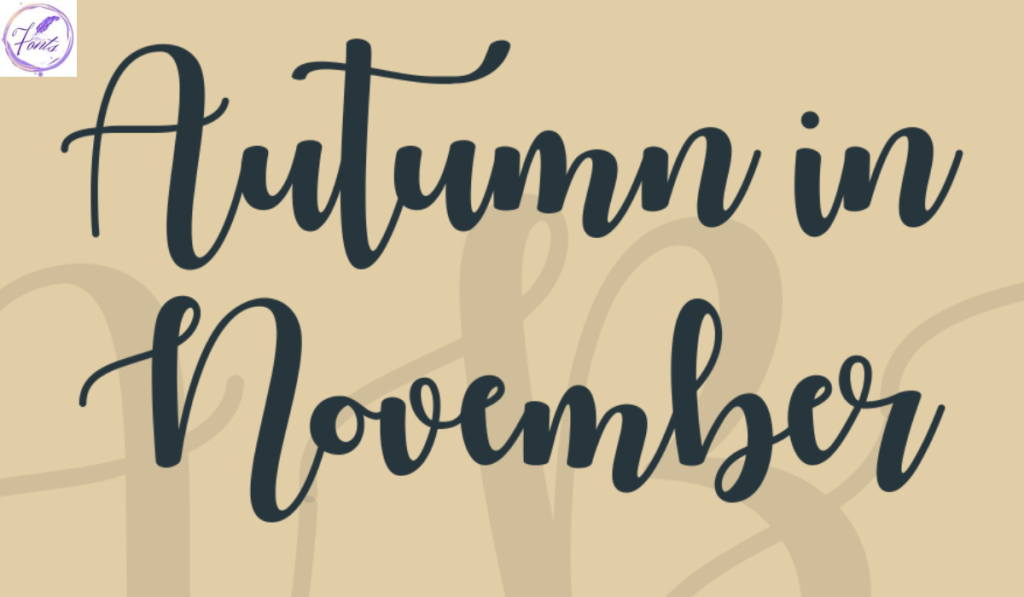
Autumn In November font việt hóa
Tác giả: Maulana Azwar
Ngày phát hành: 2019
Ngôn ngữ: Hỗ trợ nhiều ngôn ngữ, bao gồm Tiếng Việt, Tiếng Anh, và nhiều ngôn ngữ khác
Bộ Font: Autumn in November
Phân loại: Cá tính, độc đáo
Kiểu chữ: Script (viết tay)
Autumn in November font là một phông chữ được thiết kế với cảm hứng từ sự lãng mạn và thơ mộng của mùa thu. Với thiết kế việt hóa, font này bao gồm đầy đủ các dấu điểm và ký tự đặc biệt của tiếng Việt, làm cho nó trở thành sự lựa chọn hoàn hảo cho các ứng dụng từ thiệp mời đến trang trí nội dung số. Đặc biệt, phông chữ này kết hợp sự mềm mại của chữ viết tay với tính đọc dễ, phù hợp với nhiều loại thiết kế.
Đánh giá autumn in november font
Autumn in November font đã nhận được nhiều đánh giá tích cực từ cộng đồng thiết kế, đặc biệt là các nhà thiết kế chuyên về mỹ thuật và truyền thông. Phông chữ này được đánh giá cao về độ linh hoạt và khả năng thích ứng với nhiều dạng nội dung khác nhau, từ in ấn đến kỹ thuật số, mang lại hiệu quả thẩm mỹ cao và sự chú ý đến từng chi tiết. Sự nhẹ nhàng và duyên dáng của nó làm tăng sự quyến rũ cho bất kỳ dự án nào.